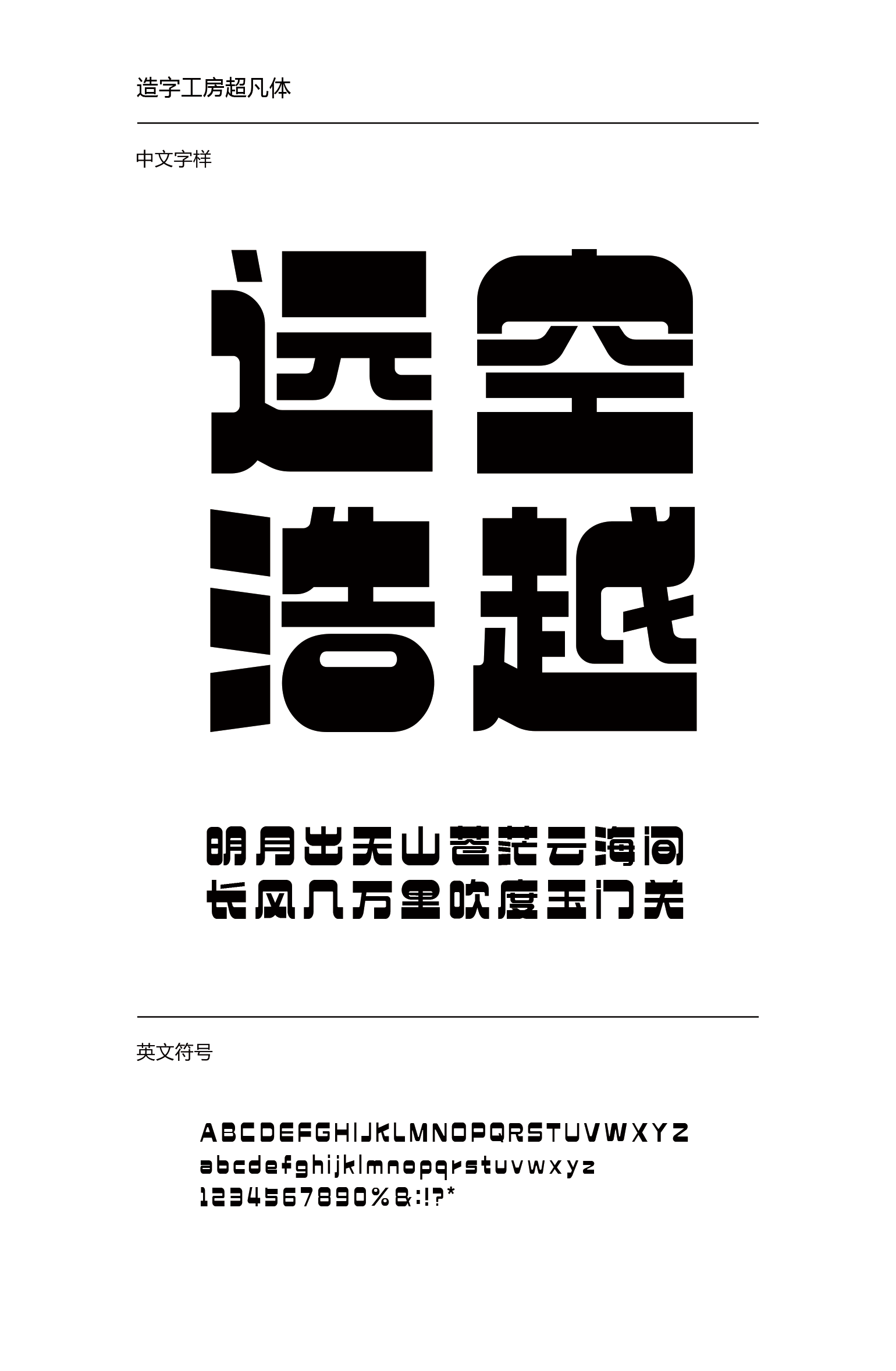
造字工房超凡体
造字工房超凡体笔画粗细对比夸张、富于变化,拐角做圆弧处理,刚毅中又平添柔和,整体方正饱满,视觉冲击力强,力量感突出,节奏分明,充满艺术张力。适用于大标题及个性品牌设计推广等环境。本字体为简体字库,采用OpenType/CID格式,Adobe-GB1-5编码。基于中华人民共和国GB2312-80字符集标准,另按需添加101个汉字。共收容字数6864CJK汉字,ASCII常用字符100个。